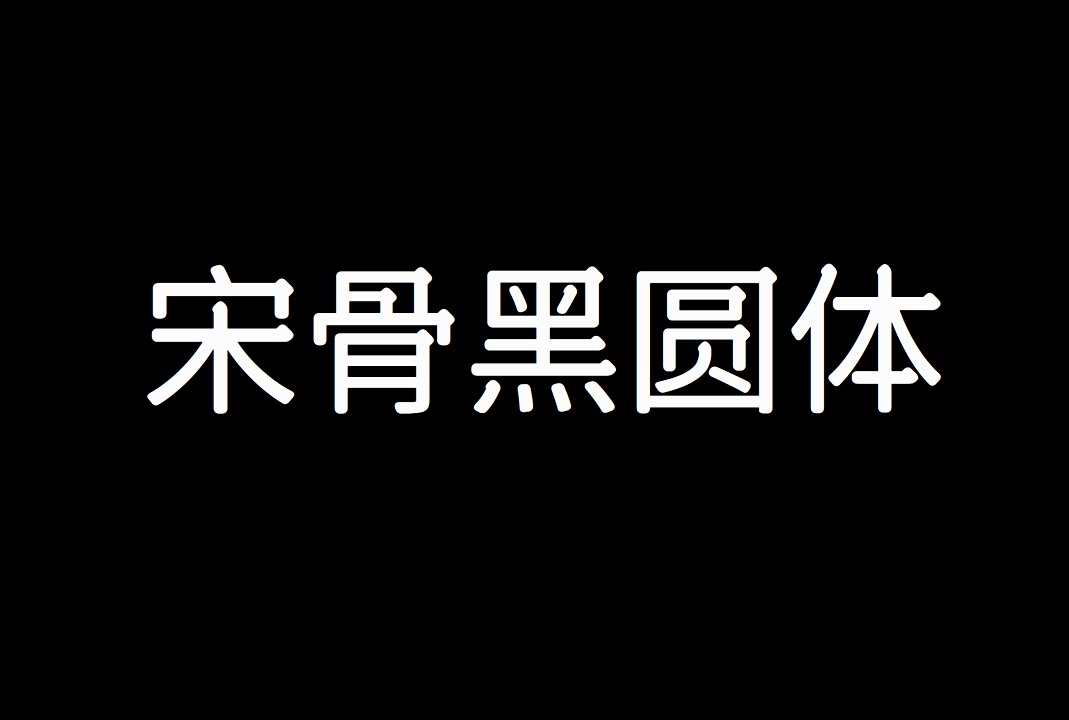
宋骨黑圆体由设计机构“奇文雲海”推出,是一款免费商用的中文字体。作为“宋骨黑体”的圆润衍生版本,它在保留原字体工整结构的基础上,对笔画末端进行了稳重且圆润的处理,巧妙融合了宋体的“骨韵”与圆体的柔和特质。
宋骨黑圆体兼具现代感与亲和力,有效解决了传统黑体在小字号下显得单调的问题,同时避免了宋体在密集排版时可能产生的繁冗感。宋骨黑圆体包含7000个常用汉字,并提供两种字重选择,适用于多种设计场景,为中文排版提供了兼具美观与实用性的优质解决方案。